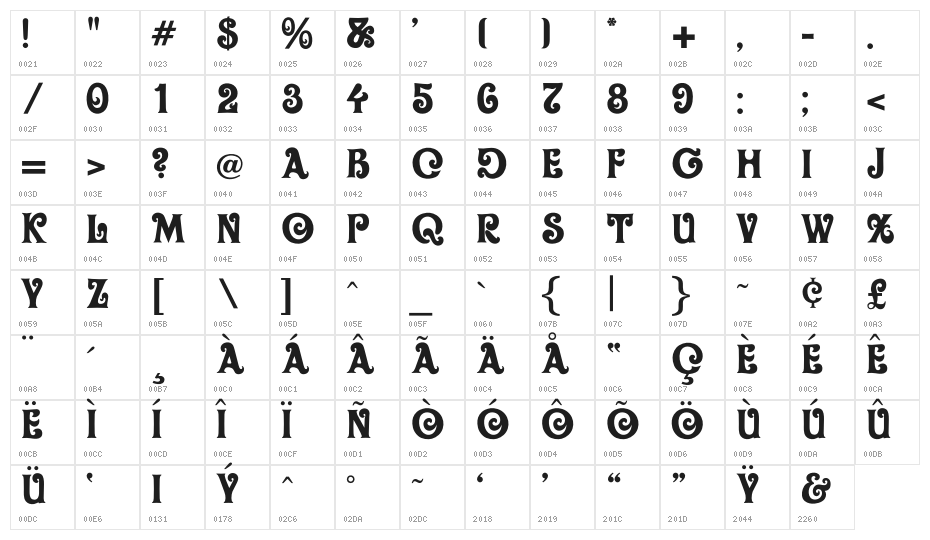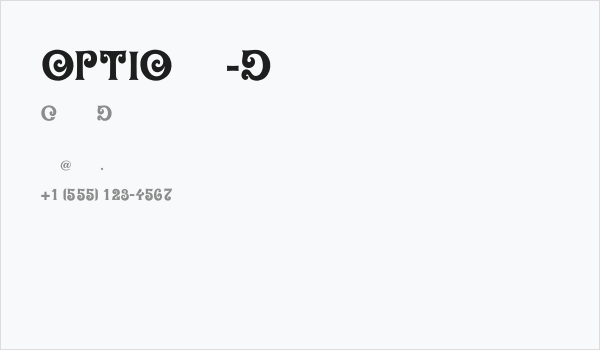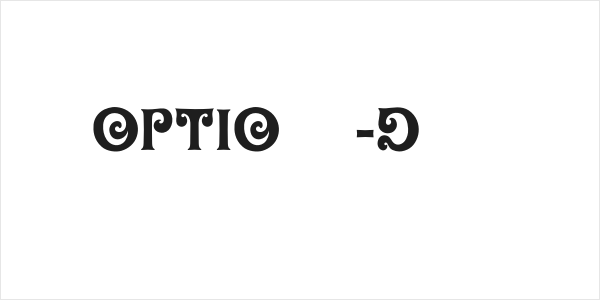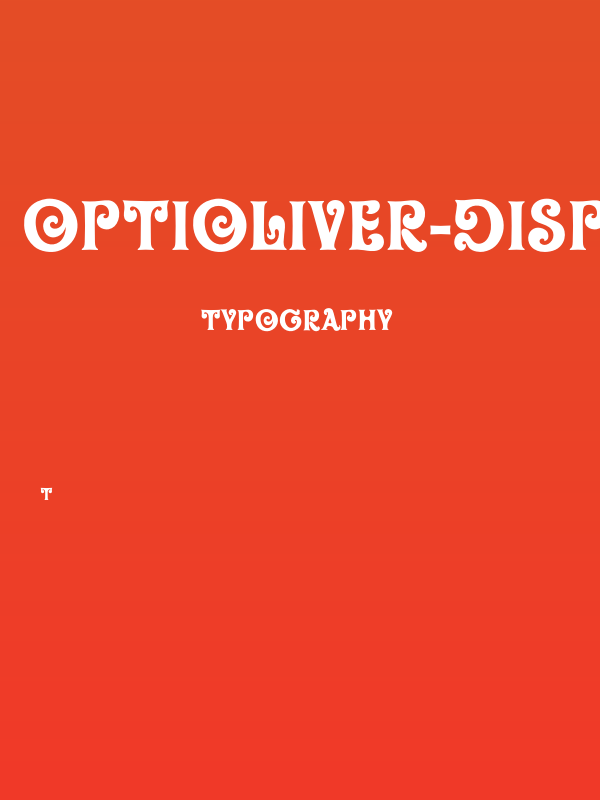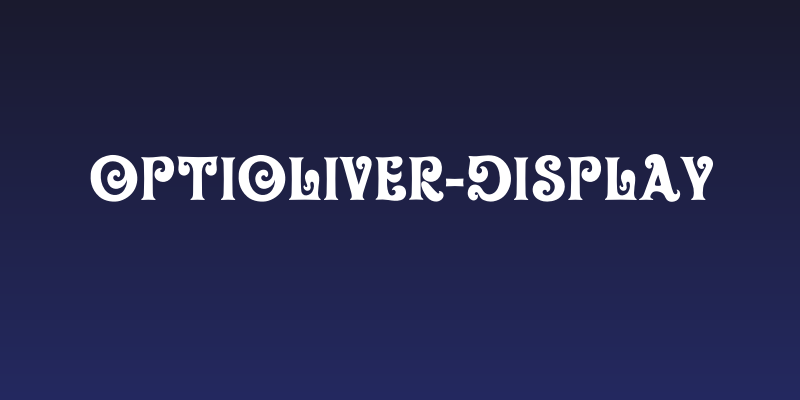
OPTIOliver-Display Font
| कंट्रास्ट | High |
| समग्र शैली | Decorative |
| उपयोग का मामला | Headlines, Logos, Posters |
| सुझाए गए प्रोजेक्ट | Ideal for use in posters, invitations, branding, and any design project that seeks to capture attention with a whimsical and artistic flair. |